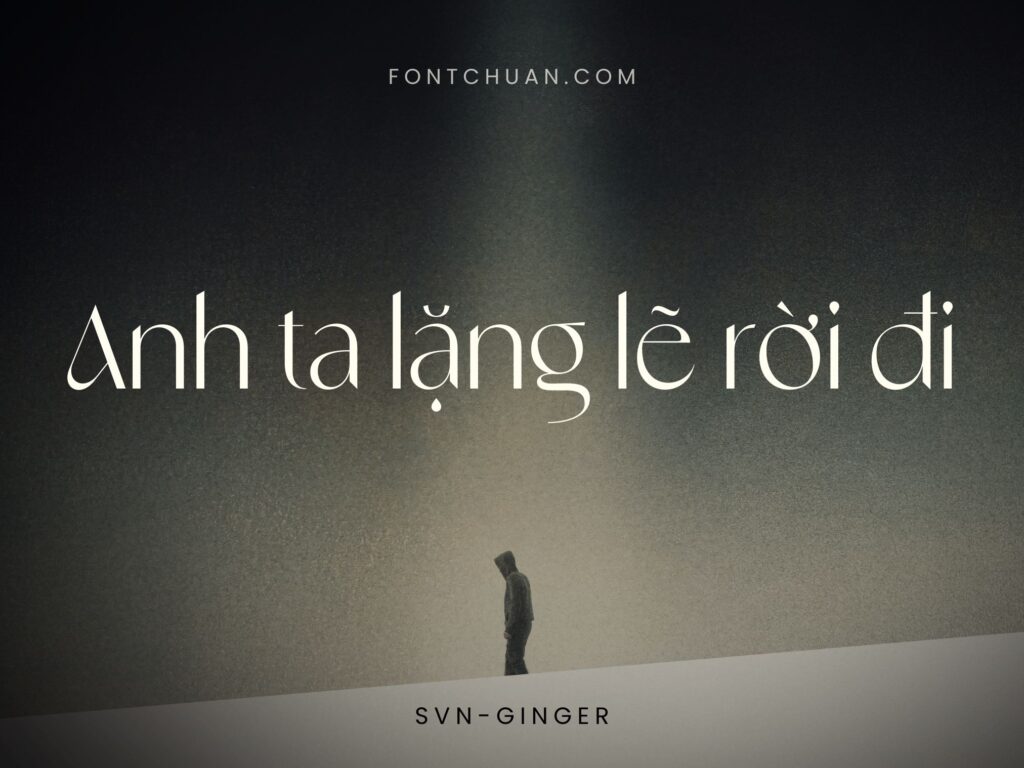
Font SVN-Ginger là phiên bản Việt hóa của kiểu chữ Ginger, được thực hiện bởi Styleno.1 Fonts. Ginger là một kiểu chữ sans-serif hiện đại và phong cách, được thiết kế bởi Sensatype. Font này nổi bật với các đường nét thanh lịch và độc đáo, giúp tạo điểm nhấn cho các thiết kế thương hiệu, logo và tiêu đề. Ginger đã được sử dụng rộng rãi trong nhiều lĩnh vực thiết kế nhờ vào tính linh hoạt và thẩm mỹ cao.
SVN-Ginger lý tưởng cho các dự án thiết kế yêu cầu sự hiện đại và chuyên nghiệp, như thiết kế logo, tiêu đề, bao bì sản phẩm và các ấn phẩm quảng cáo. Các ngành nghề như quảng cáo, công nghệ và giáo dục có thể tận dụng font này để tạo điểm nhấn trong thiết kế. Ngoài ra, font cũng phù hợp cho các sự kiện như Tết, Giáng sinh, Valentine và các lễ hội khác.